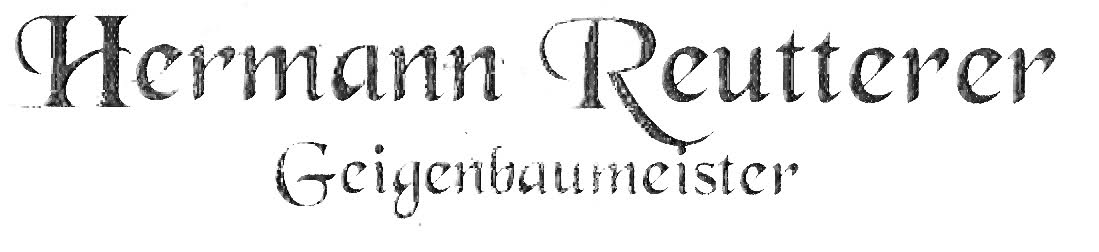
Vielleicht habt ihr einen Tipp welche Schriftart das ist bzw. wäre.
Meine erste Vermutung war: Mentor
Die ist es jedoch nicht habe schon bei myfonts nach gesehen leider bin ich da nicht fündig geworden.
... einer der ersten Freefonts …
Echt? Wie alt ist denn die Black Chancery ungefähr schon? (Hab auf die Schnelle nichts gefunden – würde mich aber mal interessieren.)
Hmmja, am falschen Fuß erwischt. Finde jetzt auch keinen Beleg mehr dazu, außer den, dass er von Elfring Fonts als Black St. Charles digitalisiert wurde und schon 1986 im Umlauf war. Also stolze 20 Jahre bereits. Mike Freiman, der in solchen Dingen sehr zuverlässig ist, sagt hier, Elfring »digitized from scratch a bunch of old typefaces, some of which nobody held the rights to any more and some that shouldn't have been made. Most of those Art Deco fonts are probably open game, though - dead designer from ancient defunct foundry.«
Ich meine mich zu erinnern, dass das Design der Schrift um die Jahrhundertwende entstand. Finde aber jetzt grad nichts dazu.
Weitere Namen zu der Schrift sollen angeblich sein: Catweazel, Whitewater, Cherries Black, Grenelefe Script, Nottingham, Tenace (SSi), Swordsman (Swfte), Caligula (GST), Dickens Script, Schwarzwald …